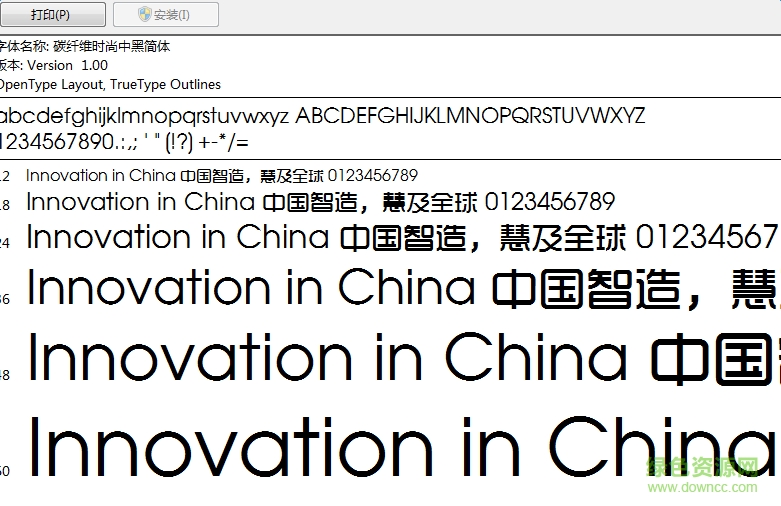
碳纖維時(shí)尚中黑簡體
碳纖維時(shí)尚中黑簡體是一款風(fēng)格時(shí)尚的黑體字體,字體極具個(gè)性,可以適用于名片設(shè)計(jì)、平面設(shè)計(jì)、廣告設(shè)計(jì)、報(bào)紙雜志、企業(yè)LOGO、商標(biāo)注冊(cè)、電視臺(tái)廣告等領(lǐng)域,有喜歡的網(wǎng)友可免費(fèi)下載收藏。
碳纖維時(shí)尚中黑簡體是一款超炫的碳纖維字體,該字體比劃均衡,端莊雅致,黑人一種簡約時(shí)尚的感覺。有喜歡的朋友趕快來綠色資源網(wǎng)下載使用吧!